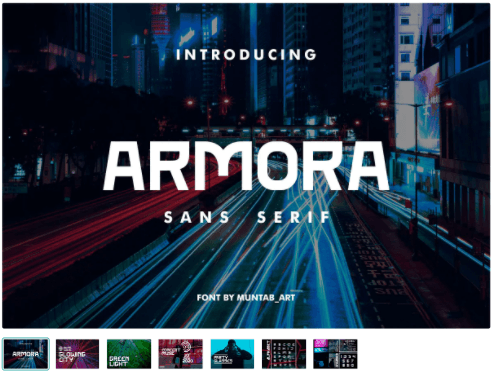
Armora | Modern Font
Шрифты Armora включают прописные буквы, цифры, большой диапазон знаков препинания. Шрифт без засечек в современном стиле. Создан для плакатов, веб-дизайна, брендинга, иллюстраций, значков и некоторых других работ.